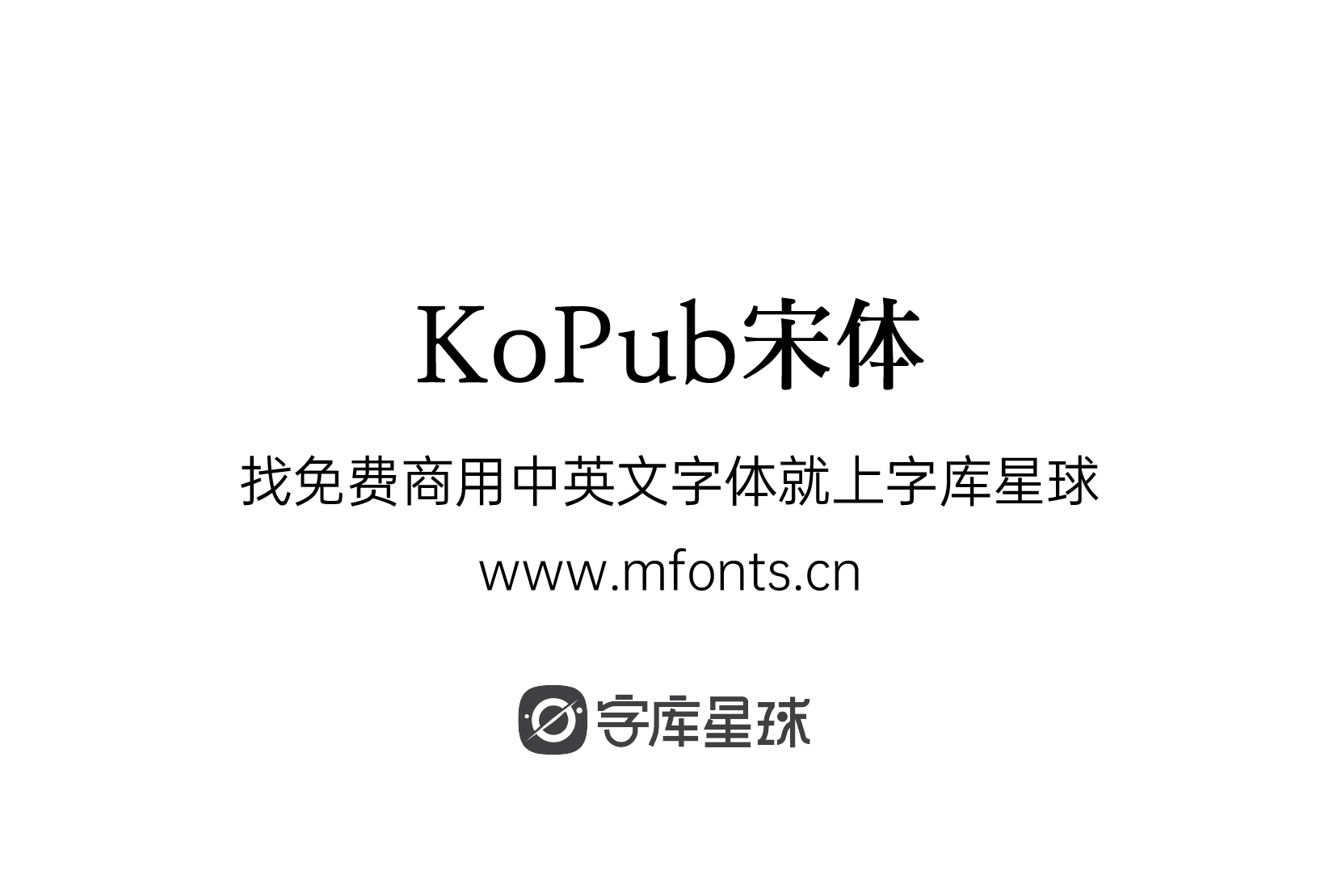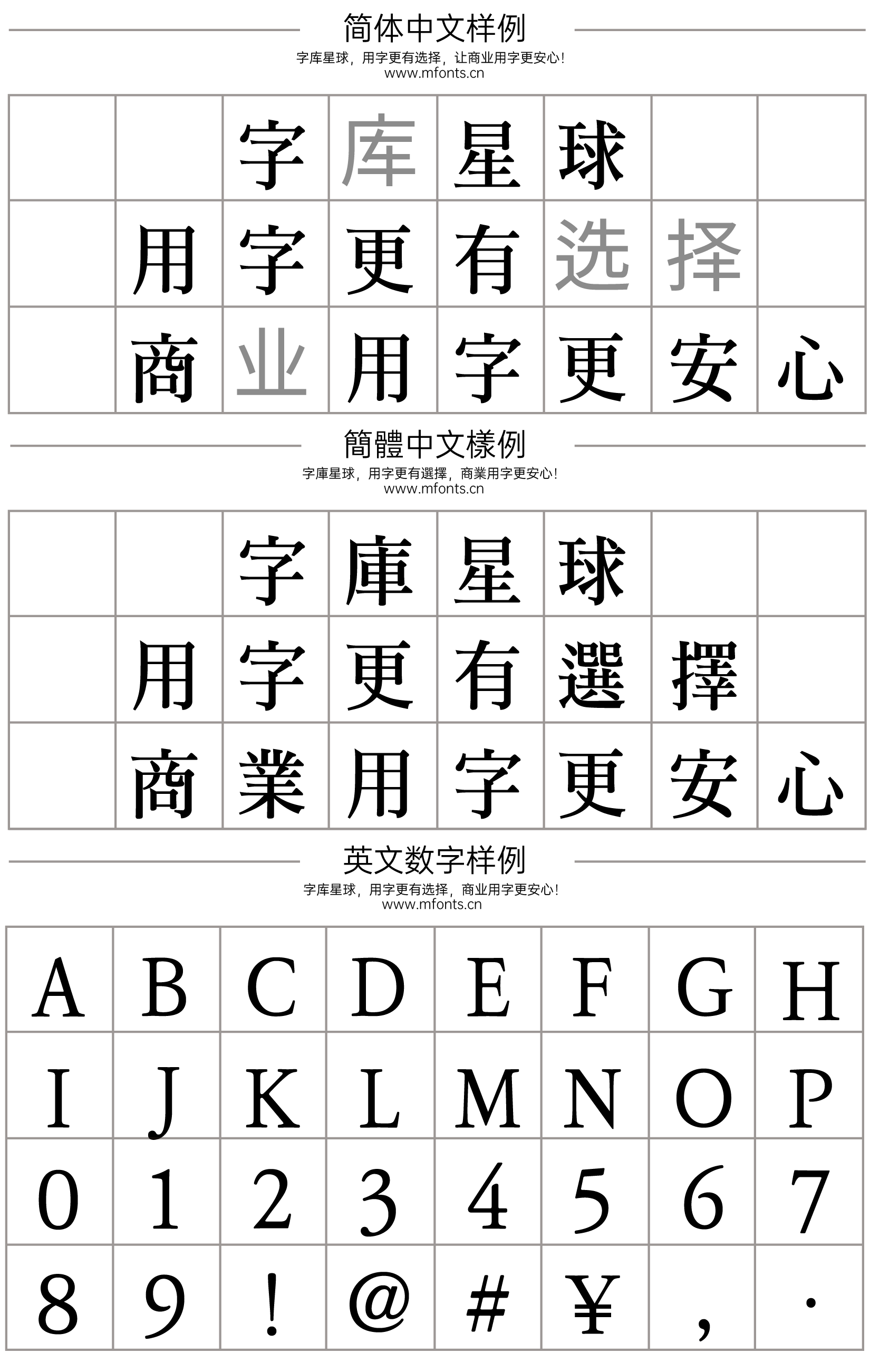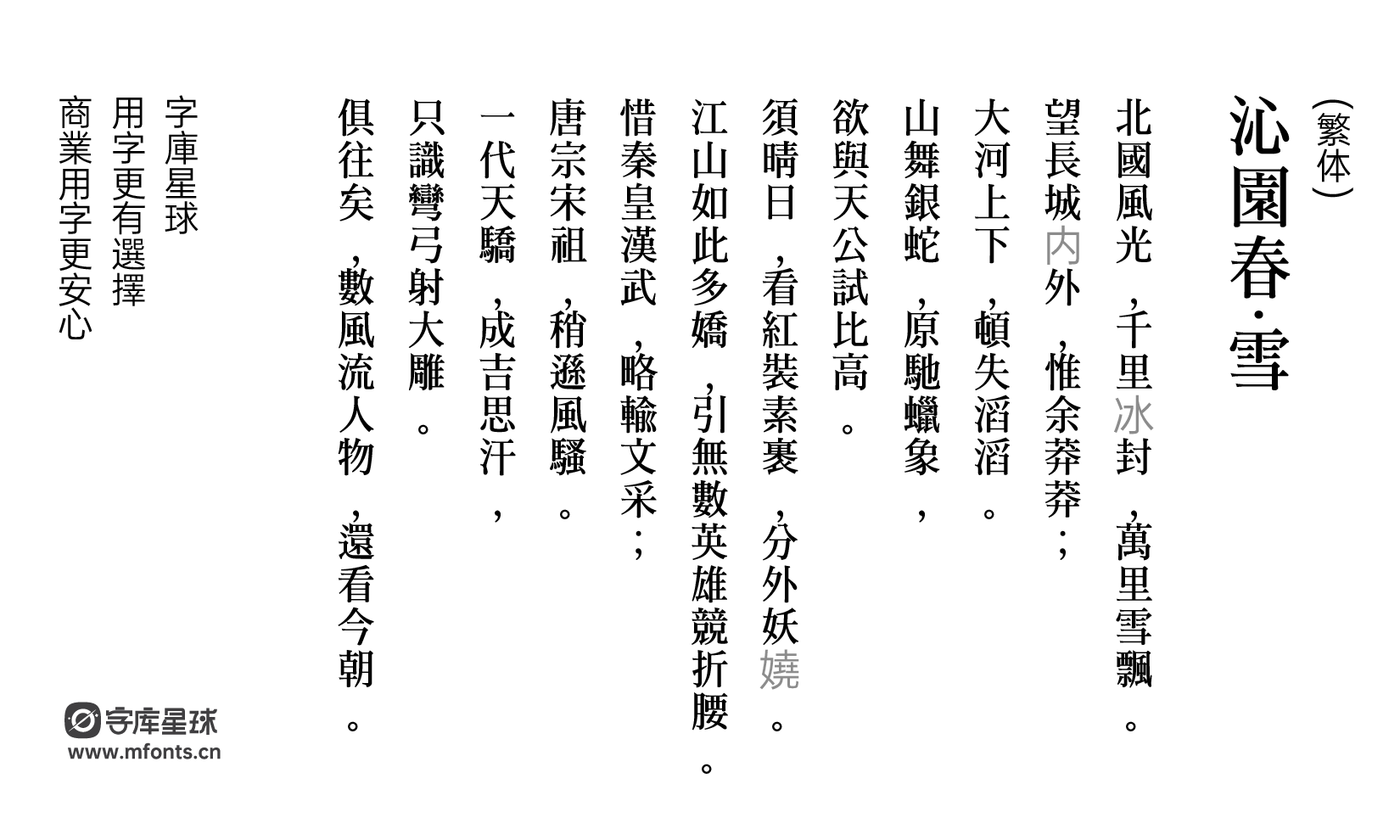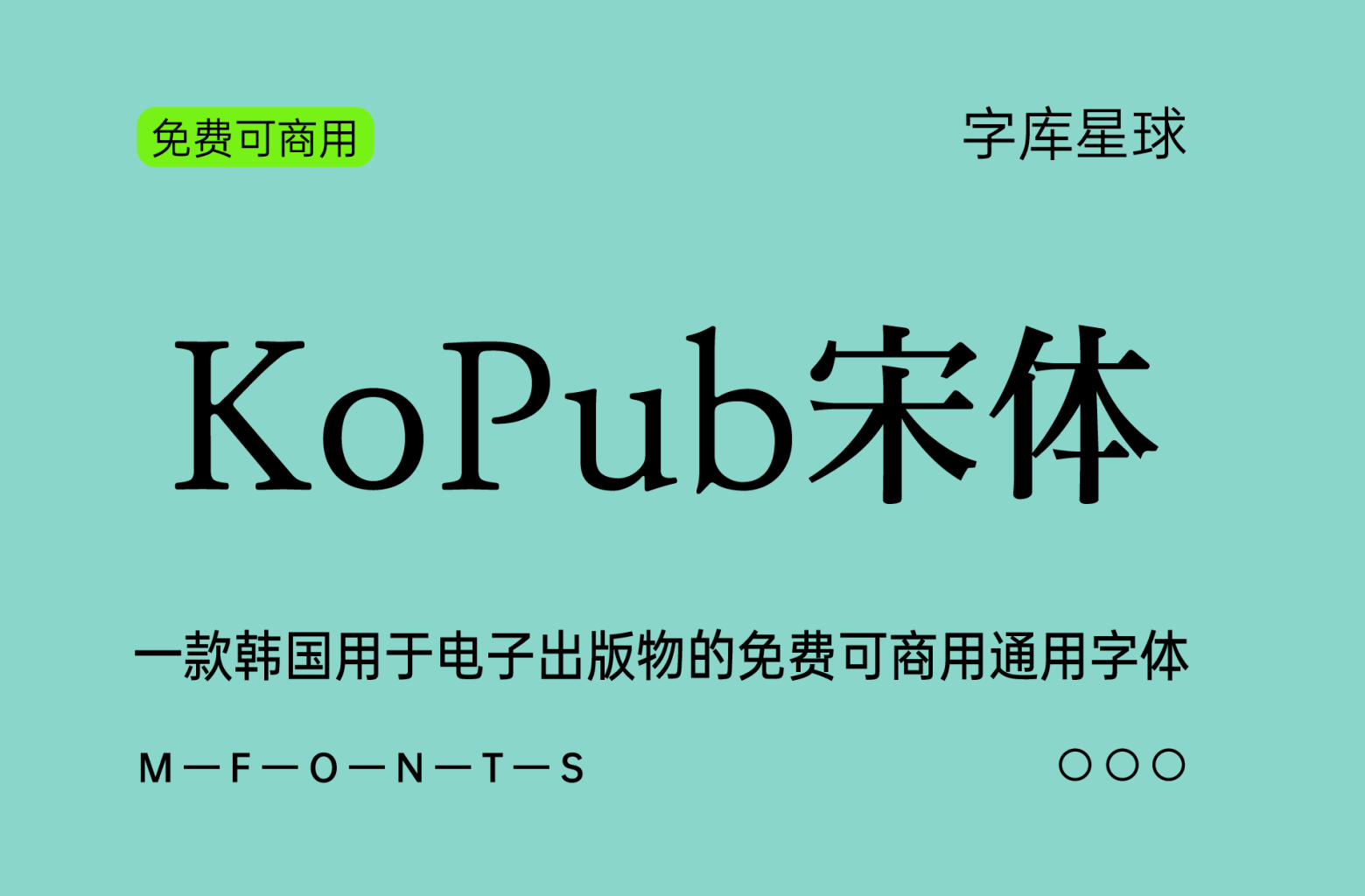
KoPub宋体
KoPub宋体综合版_KoPub字体+多语言与书籍或报纸等印刷材料不同,电子书只能在数字屏幕上查看,因此需要专门的字体。据此,韩国出版协会于2011年免费开发并分发了“KoPub字体”,目的是加强出版商的电子出版内容制作,振兴电子书市场。
“KoPub 字体”在数字屏幕上显示出与印刷材料一样好的可读性,并且已成为名副其实的最佳字体,不仅用于出版业,而且还用于 IT、电影、和广告设计。
2019 年,“KoPub 字体”重生为“KoPub World 字体”。
“KoPub World 字体”包含多种语言,包括扩展汉字、日语、拉丁语、俄语、希伯来语、阿拉伯语和梵语,以及迄今为止尚未实现的旧韩文,让读者享受更广泛的范围知识和文化生活。
通过‘KoPub World字体’,我们希望将国内的优秀内容介绍到海外,把来自世界各地的各种好书分发给我们的读者。